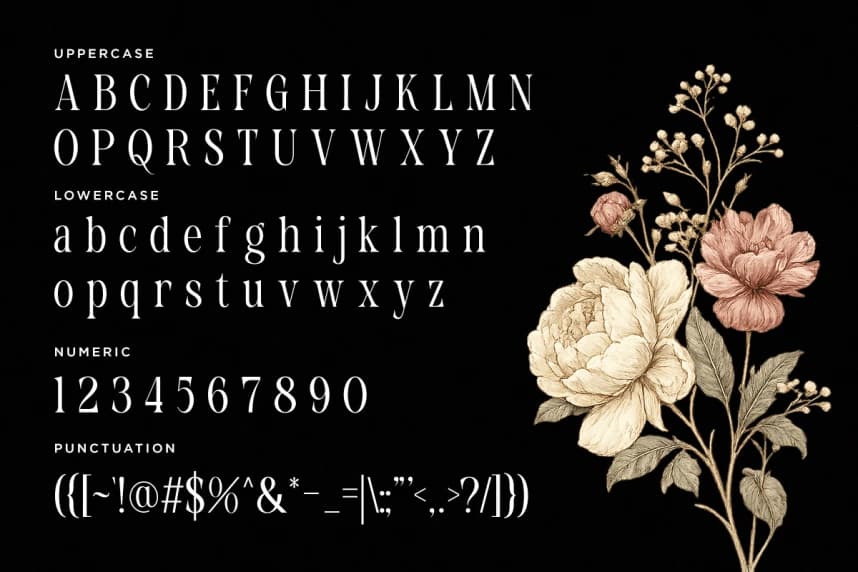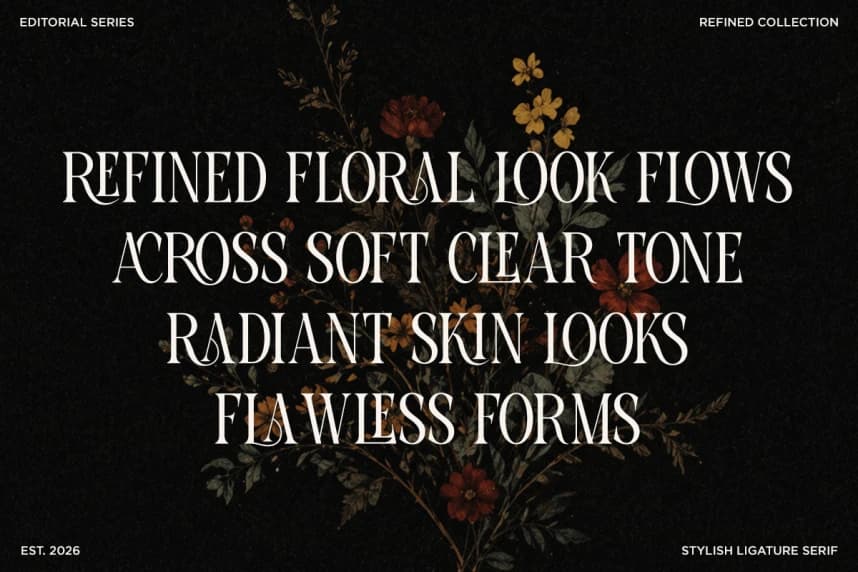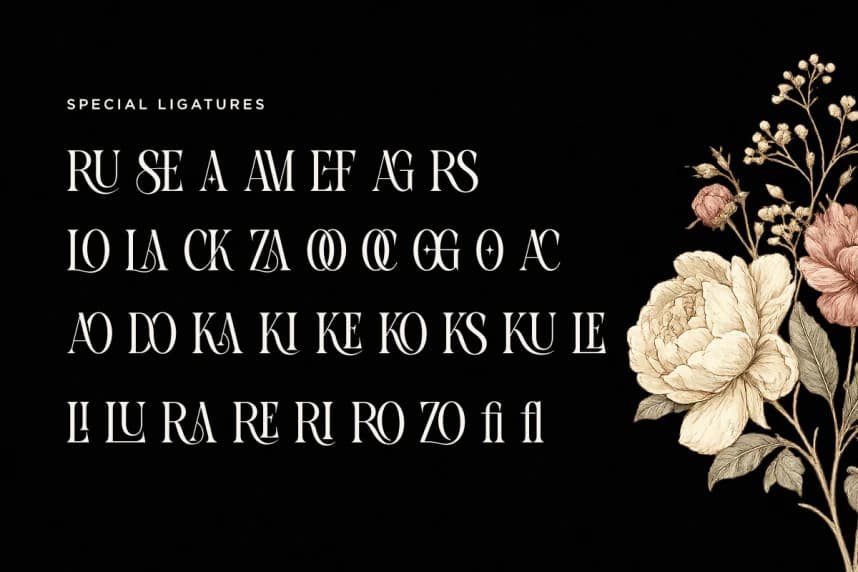
Black Cruise Font
Black Cruise Font, zarif bir ligatür serif yazı tipidir ve her tasarım projesine zarafet, lüks ve sinematik güzellik katmak için özenle tasarlanmıştır. Zarif eğrileri, sanatsal ligatürleri ve yüksek kontrastlı serif detaylarıyla öne çıkar.
Black Cruise Font, her tasarım projenize zarafet, lüks ve sinematik güzellik katmak için özenle tasarlanmış şık bir ligatür serif fontudur. Nazik eğrileri, sanatsal ligatürleri ve yüksek kontrastlı serif detaylarıyla